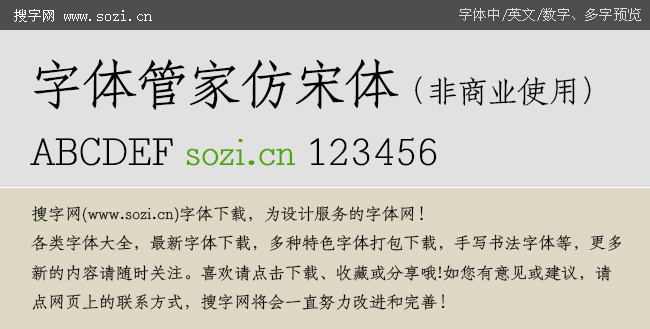
字體管家仿宋體(非商業(yè)使用)
搜字網(wǎng)給大家提供一款字體管家仿宋體(非商業(yè)使用)中文字體下載,字體管家仿宋體(非商業(yè)使用)是一款字形清秀的中文字體,該字體結(jié)構(gòu)優(yōu)美,識別性好,適合海報設(shè)計、包裝畫冊等宣傳廣告等應(yīng)用(此字體為個人非商用版,商用可以聯(lián)系QQ:1006760504)。